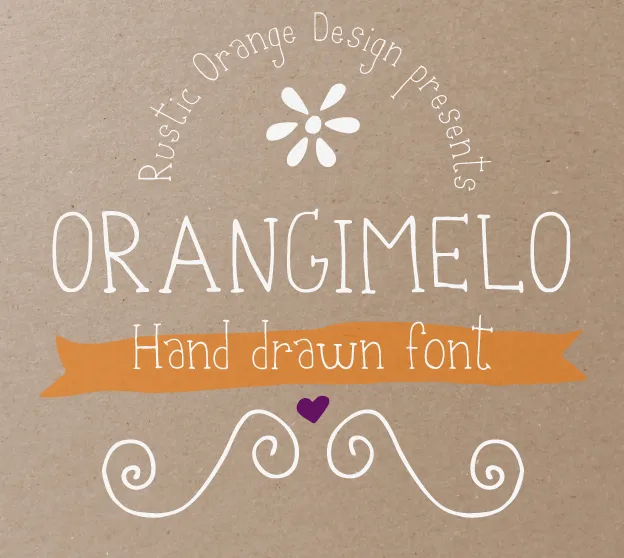
A Orangimelo Hand Drawn Font é uma fonte script que transmite leveza e naturalidade, combinando elementos ágeis com linhas suaves. Ideal para criações artísticas ou editoriais, essa fonte oferece um toque distintivo e elegante que combina perfeitamente com estilos de design modernos e vintage. Suas curvas fluidas e traços delicados garantem uma aparência única que se destaca em qualquer projeto visual, seja ele editorial, gráficos publicitários ou criações digitais. Esta fonte é perfeita para quem busca um equilíbrio entre graça e profundidade em seus projetos de design, proporcionando uma experiência de escrita única e divertida. Não hesite em explorar a Orangimelo Hand Drawn Font; ela certamente adicionará um toque especial ao seu próximo projeto criativo.